2020年10月20日下午王茵甲骨文书法作品字库上线新闻发布会在北京泰文楼美术馆圆满成功召开,同时举办为期7天的王茵甲骨文书法作品展。中国楹联学会书法艺术研究会发来贺信。此次活动由安阳殷墟博物馆、王茵甲骨文书法屋(上海翱墨文化传播有限公司)、北京有字库网络科技有限公司、北京泰文楼美术馆主办,国宝工呈(北京)艺术品鉴定有限责任公司、浙江好诚明企业服务有限公司、浙江娱米文化传媒有限公司、浙江鎏亚文化有限公司、浙江三立集团、汇龙珠宝、侣程网等单位协办。学术指导单位: 中国书法家协会、中国美术家协会、中国艺术研究院、中国楹联学会书法艺术研究会、中国美术馆、中国国家博物馆。
安阳殷墟博物馆李文静主任赠送甲骨文原片模型给甲骨文书法家王茵老师
开幕式现场,安阳殷墟博物馆主任李文静女士,中国楹联学会书法艺术研究会主任裴令前先生,国宝工呈(北京)艺术品鉴定有限责任公司总经理闫利萍女士,著名音乐人张俊老师和丰珊珊老师等领导与嘉宾参加了王茵甲骨文书法作品字库上线的剪彩仪式。
此次王茵甲骨文书法作品字库,共收录了500个王茵老师书写的甲骨文书法字,并于2020年9月28日在"字客网"正式上线并提供下载。
在活动现场也举办了王茵老师将甲骨文书法作品"甲骨文明 一鸣天下"捐赠给安阳殷墟博物馆的捐赠仪式。
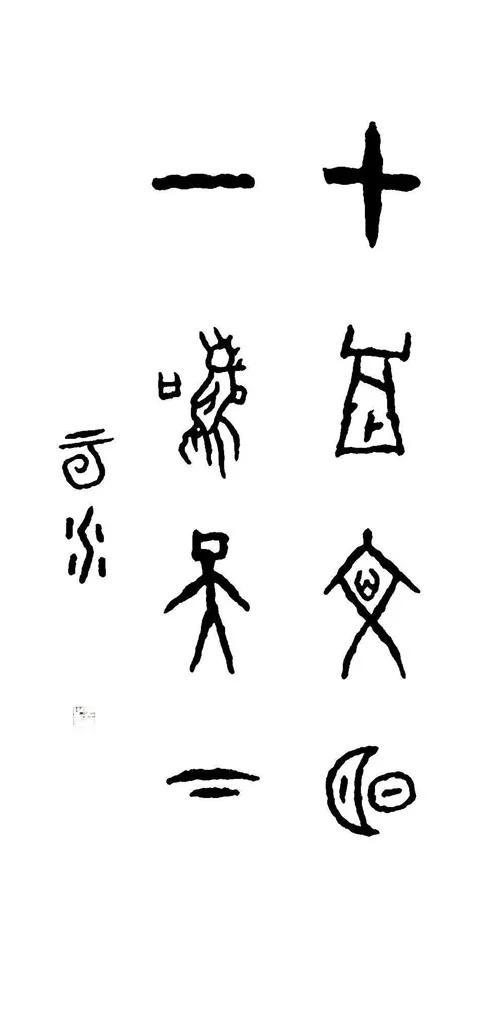
紫砂壶大师陆明生老师、面塑大师梁岗子老师、树皮画汪吉鹏老师、青铜器收藏大家蔡彤彦老师在活动现场向嘉宾们介绍了如何将自己的艺术门类与甲骨文书法艺术融合。
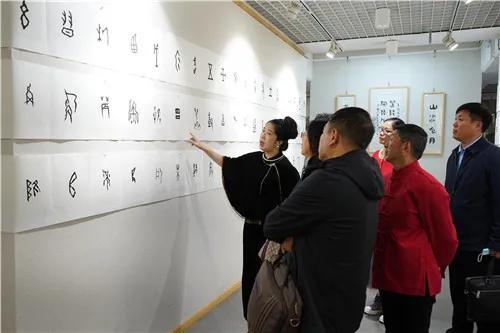
王茵,浙江杭州人,国家一级书法师、甲骨文书法屋非遗创始人、中国国宾礼艺术家、中国楹联学会书法艺术研究会会员、中国楹联学会《中华国粹》诗词理论专刊副主席、中国书画家协会理事、CCTV老故事频道筑梦空间栏目艺术顾问、中国书画家联谊会新文艺群体书画家工作委员会委员、北京华夏邦交国礼书画院院士、孔子美术馆客座教授。王茵老师自幼喜欢中国传统文化特别是书法艺术,学书法从颜楷入手,又习二王、米芾、黄庭坚、怀素等各时代书法名家,后又主攻石鼓文、散氏盘、秦筒、帛书、汉印等,现致力于甲骨文书法的学习和研究。书法作品赏心悦目、浑厚凝重、气息古朴、意趣生动、格调高雅、法度谨严,书法线条变化多端气象万千。王茵老师深入研究古人的甲骨文字,完全尊寻古人刻在甲骨上的笔法和意境用毛笔书写在宣纸上,并在墨法、心法上进行了研究尽量创作出与古人甲骨文字原汁原味的甲骨文书法作品来。
在书写这些甲骨文字时,让王茵老师深受感动、震撼和惊喜,没想到在三千年前我们伟大的中华民族就拥有了如此辉煌灿烂的甲骨文明,王茵老师认为甲骨文的学术价值和美学价值已经达到了非常高的高度。而且在学习研究推广甲骨文书法时,王茵老师发现甲骨文可以激发起国人的自信心、民族自豪感和凝聚力,是很好的爱国主义教育的题材。王茵老师认为甲骨文不仅仅是祖先留给我们的一座文化宝藏更是一座非常宝贵的精神宝藏,甲骨文明一定会在中华民族伟大复兴的过程中贡献出自己的力量。
为了进一步推广甲骨文书法艺术,王茵老师还研制了甲骨文书法作品的各类艺术衍生品。例如刻有甲骨文书法作品的紫砂壶、玉佩、书签、钢笔等等,让甲骨文书法艺术深入到人们的生活中去,让人们随时可以观看到和感悟到甲骨文书法之美。
最后王茵老师表示今后会更加努力地学习和研究甲骨文,尽量把已经认出的甲骨文字都用毛笔书写出来,并且要不遗余力地传承和推广甲骨文书法艺术,为中华民族的伟大复兴贡献出自己的一份力量。(来源高文玉视点)